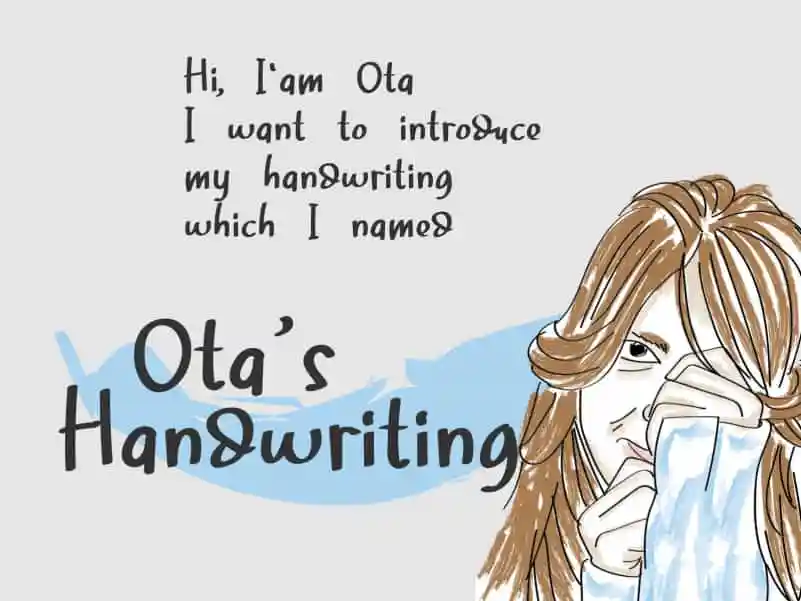
Ota’s Handwriting Font – Fonte Grátis
Ota's Handwriting Font
A fonte ‘Ota’s Handwriting Font’ é uma elegante escolha para aqueles que buscam criar designs singelos e delicados. Ela tem traços bem equilibrados, trazendo beleza a cada caractere. Suas linhas são fluidas e fluidas ao mesmo tempo suave e forte, o que a torna uma opção ótima para designers criativos de todos os tipos. Quando adicionada às suas mais audaciosas ideias, é notável como ela as faz surgir vivos e reais. Esta fonte é perfeita para projetos onde uma escrita manuscrita delicada pode complementar um design inovador ou trazer a sensação de um autêntico caderno de anotações. Nuryanto Dwi, o designer desta fonte, conseguiu capturar um estilo único que vai do elegante ao sofisticado, sempre mantendo uma fina linha entre ser acessível e inspiradora.